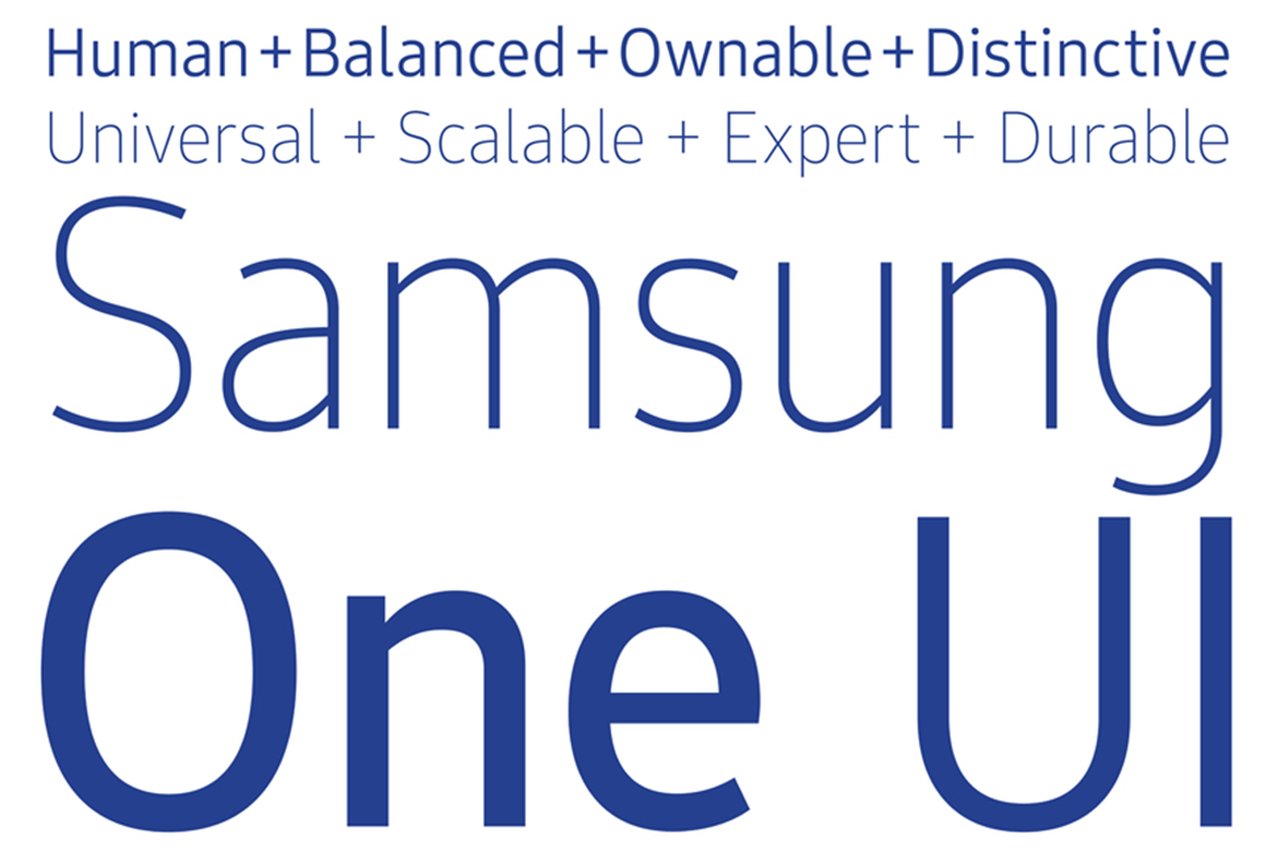
Mancava solo Samsung all’appello dei colossi tecnologici con il proprio font: tra Google e il suo Roboto, Apple con San Francisco e Microsoft con Segoe, ecco che arriva SamsungOne.
Il nome non è forse dei più originali, ma l’obiettivo di questo font è chiaro come i suoi caratteri: cercare di dare un’identità unica e visibile a tutti i prodotti Samsung; SamsungOne è stato creato per essere utilizzato su tutti i prodotti Samsung, e per essere perfettamente leggibile sia su piccoli display come quelli degli smartphone che su grandi pannelli come gli schermi televisivi.
SamsungOne supporta già oltre 400 linguaggi, per un totale di oltre 25000 caratteri differenti; paragonato con Roboto, SamsungOne differisce per alcuni particolari, come ad esempio “c”, “s” e “a” meno chiuse e una “l” non completamente dritta: il risultato lo potete vedere qui sotto.
Non si sa ancora quando questo nuovo font arriverà sui prodotti del colosso coreano, anche se sono in molti ad attenderlo già sul nuovo Samsung Galaxy Note 7; nel frattempo fateci sapere cosa ne pensate di SamsungOne, con un commento qui sotto.